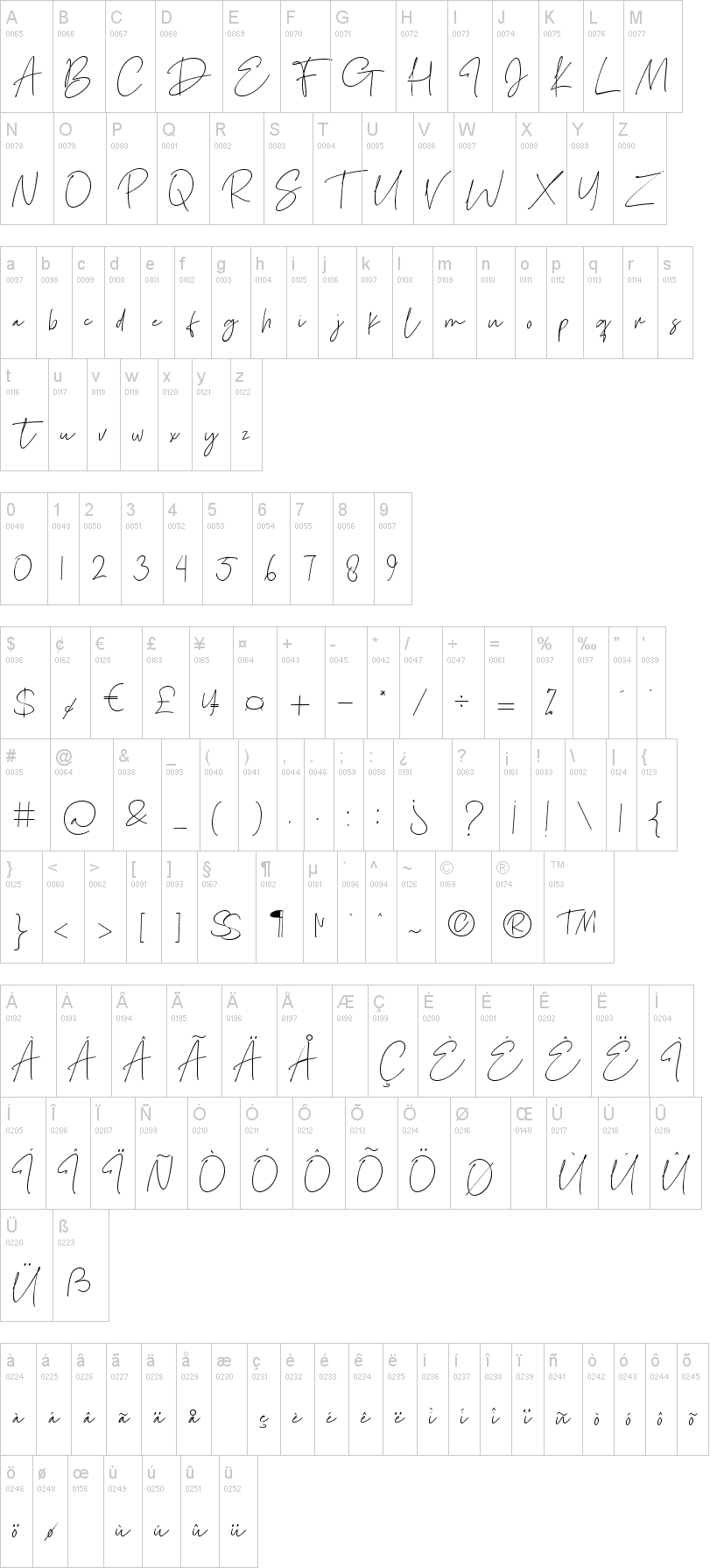
Le Festin 是一种美丽的手写风格字体,由来自法国的设计师 Ludovic Fauchet 创建。这个字体以其流畅的连笔和轻盈的笔画著称,非常适合用于印刷品、海报、包装设计等需要独特、有吸引力的视觉效果的设计项目。Le Festin 字体包含大写和小写字母、数字和标点符号,是一款非常多用途的字体。此外,这个字体还提供了多种不同的风格和变体,包括粗体、斜体和手写风格等,让您可以更轻松地适应不同的设计需求。内容介绍
Le Festin是一款非常不错的手写艺术字体,具有很好的视觉感,适合于文化类的宣传设计、商业类品牌的广告和产品包装设计以及个性化文字排版等较多场景。